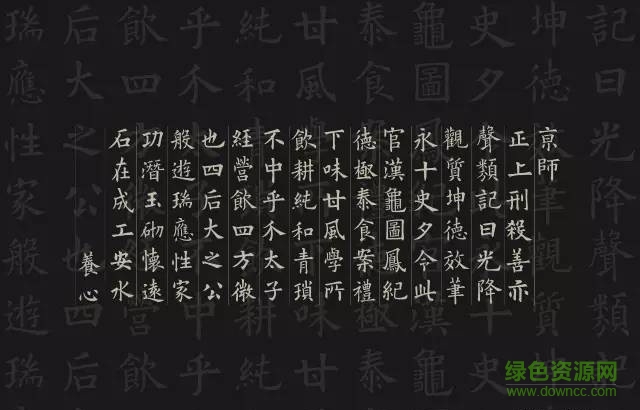
漢儀歐楷
漢儀歐楷字體是一款漢儀類正規(guī)楷體風(fēng)格字體軟件,歐楷體一筆一畫一絲不茍,粗細(xì)相間,優(yōu)雅氣息十足,非常的醒目養(yǎng)眼,還有更多類似好看字體歡迎來綠色資源網(wǎng)下載體驗(yàn)!
漢儀歐楷字體是一款應(yīng)用于藝術(shù)設(shè)計(jì)方面的簡體中文字體,該字體筆畫粗壯,尾部的甩尾有力且有豐富的筆觸細(xì)節(jié),大字效果突出且引人注目;并且最大程度還原作者書寫字形,細(xì)節(jié)表現(xiàn)完整,且字庫完整,可以廣泛應(yīng)用于名片設(shè)計(jì)、新聞媒體、宣傳海報(bào)、ppt、影視制作以及內(nèi)容用字等領(lǐng)域。
該字體粗細(xì)相間,給個(gè)字所占空間大小一致,盡顯楷體的正規(guī),整體效果十分優(yōu)美好看,用來裝帥再合適不過了!